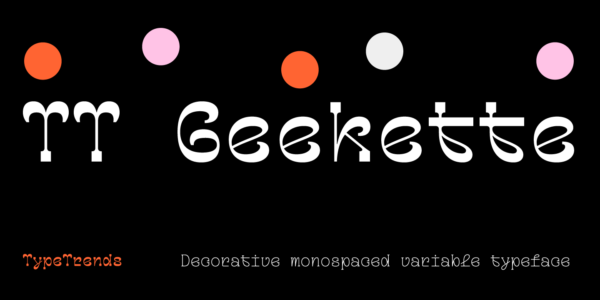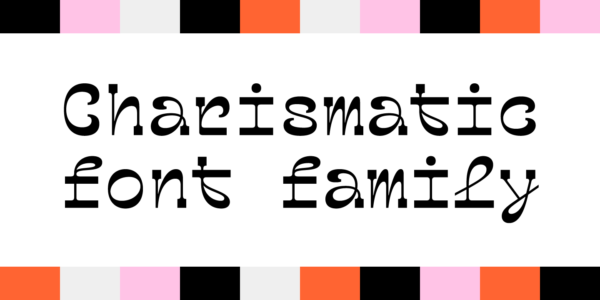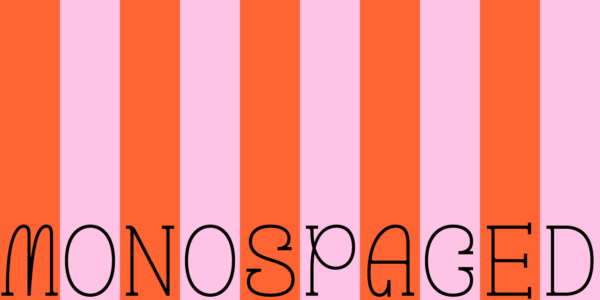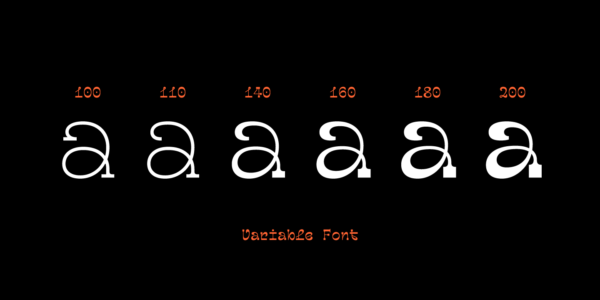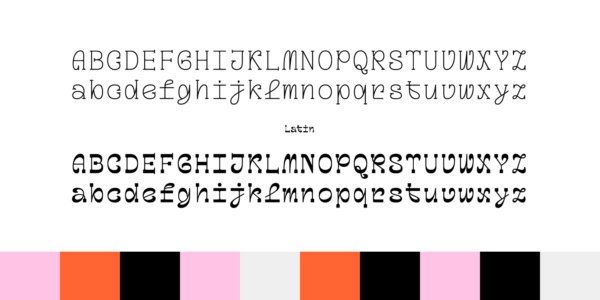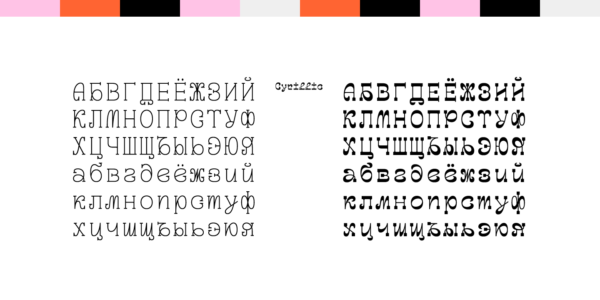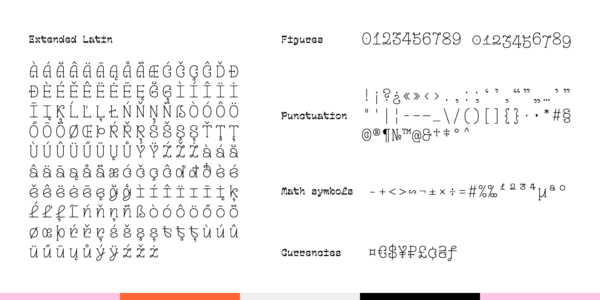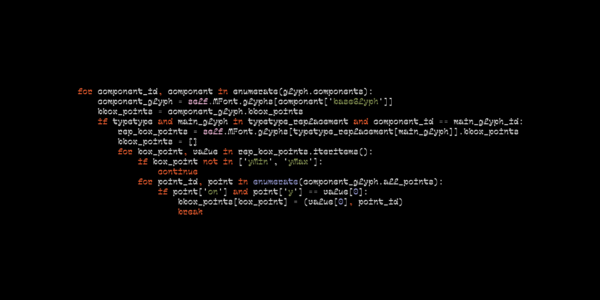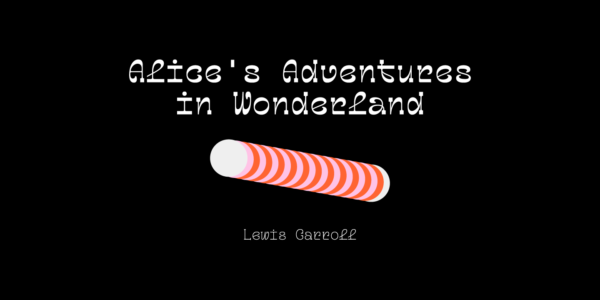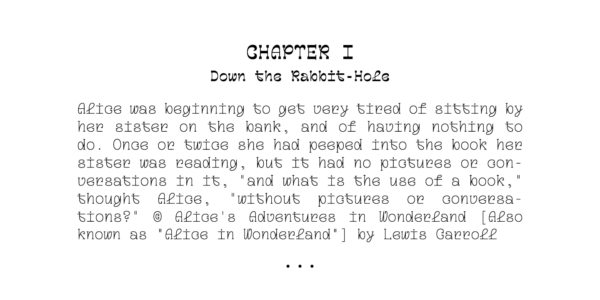
TT Geekette
TT Geekette — ТТ Гикетт
Произносится «ТТ Гикетт». «Geekette» — производное слово от geek (с английского «гик», человек, увлеченный технологиями) и уменьшительного женского суффикса -ette. Буквы «TT» являются аббревиатурой названия компании.
TT Geekette — экспериментальный декоративный шрифт с уникальной графикой и дружелюбным характером. С помощью вариативного начертания можно менять его внешний вид.
TT Geekette
Вариативная антиква с пластичными формами знаков
TT Geekette
В этом проекте мы хотели уйти от упрощений и сухой геометрии и поэкспериментировать с плавностью, мягкостью и пластичностью форм. Вариативность в TT Geekette влияет наращивание контраста — вы постепенно проходите путь от полностью не контрастного монолинеарного шрифта с засечками, к шрифту с ярко выраженным обратным контрастом. Семейство TT Geekette состоит из 3 шрифтов.
О гарнитуре TT Geekette
TT Geekette — вариативная антиква с дружелюбным характером. Это экспериментальный проект, в рамках которого мы хотели уйти от упрощений сухой геометрии и поэкспериментировать с плавностью, мягкостью и пластичностью форм. А чтобы шрифт стал чуть более стильным и серьёзным, мы сделали его моноширинным.
При разработке TT Geekette мы хотели переосмыслить графический подход к созданию антикв (serif) и отказались от классического приема рисования, построенного на логике письма пером. В его дизайне есть несколько системных приёмов, например, «петли», которые задают пластический ритм. Графика TT Geekette уникальна — это оригинальный и неповторимый шрифт, который не похож на другие.
С помощью ползунка регулировки оси вариативности в TT Geekette можно наращивать контраст, проходя путь от неконтрастного монолинеарного шрифта с засечками к шрифту с ярковыраженным обратным контрастом. Наличие засечек тоже опционально — в вариативном шрифте их можно убрать.
TT Geekette — декоративный шрифт, который подходит для печатной продукции, брендинга и веб-дизайна. Например, его можно использовать для оформления вывесок кафе и ресторанов, упаковок продуктов питания, плакатов и киноафиш, пригласительных на мероприятия. Кроме того, его можно использовать в программировании — хорошее настроение будет вам обеспечено!
Семейство TT Geekette состоит из трех шрифтов: монолинеарный TT Geekette Bones, антиква c обратным контрастом TT Geekette Muscles и вариативный TT Geekette Variable. В состав каждого начертания входит более 450 глифов.